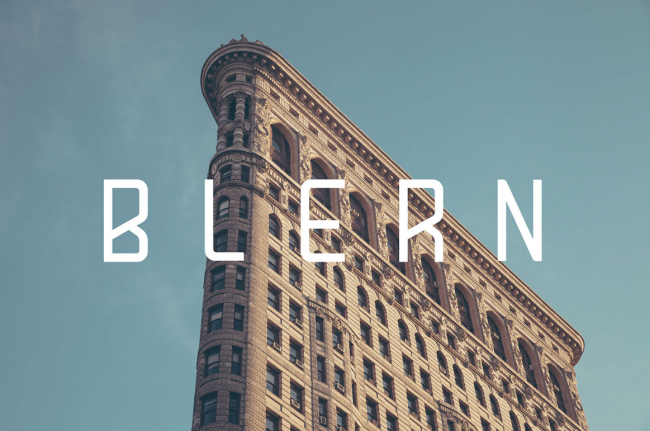
デザイナーにおすすめの、クリエイティブなフリーフォント20個を紹介します。
いずれもオリジナリティのあるデザインが特徴です。他とは一味違う、独創性のあるデザインになります。
Blern
モダンなデザインのセリフフォントです。ビジュアルデザインに合わせやすい、安定したバランスです。
Bajern
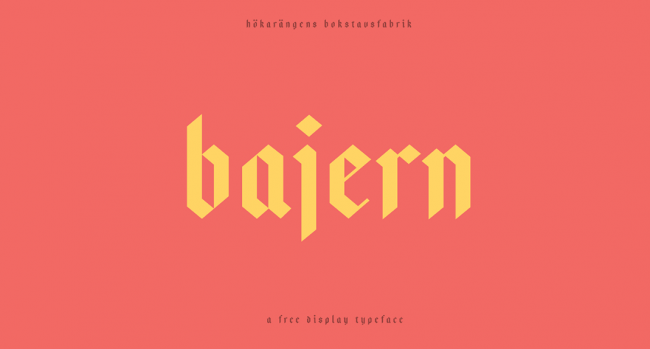
Bajern
直線でデザインされた、オリジナリティのあるデザインのフォントです。写真ギャラリーなどのモダンなデザインに合います。
Break
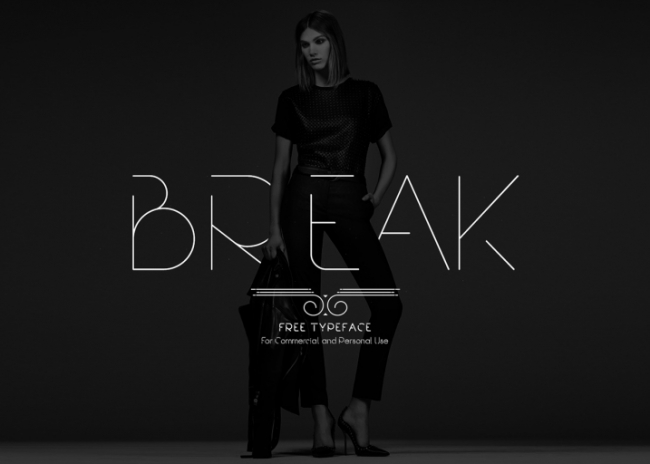
Break
Anurati
文字が欠けているという、とても独創的なデザインのフォントです。デザインに、神秘性と未来的なイメージを出すことができます。
Glamor
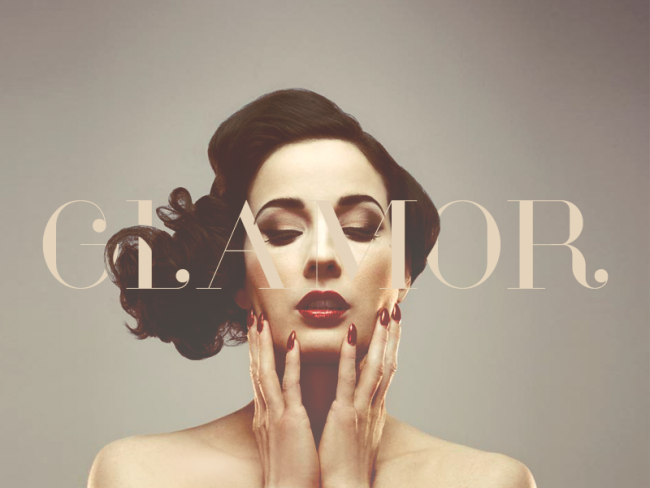
Glamor
モダンでエレガントなデザインのフォントです。デザインに高級感を出したいときにおすすめです。
Yikes
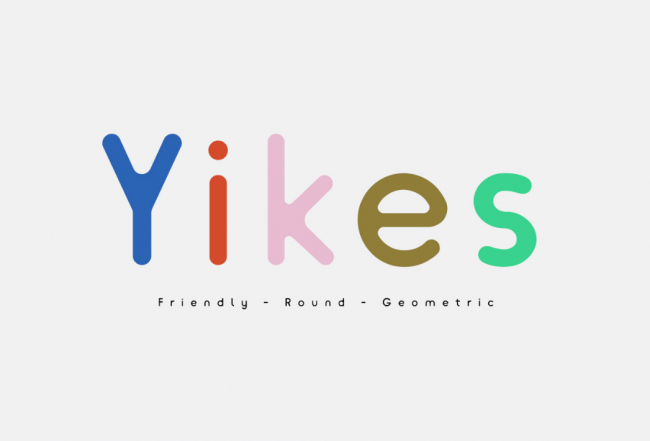
Yikes
先端や繋ぎ部分の丸みが特徴的な英語フォントです。ロゴやプロダクトデザインにもよく合います。ダウンロードリンクが小くなっていますが、「STEP 2: DOWNLOAD THE FILE HERE –> CLICK」と書かれている部分からダウンロードできます。
Soria
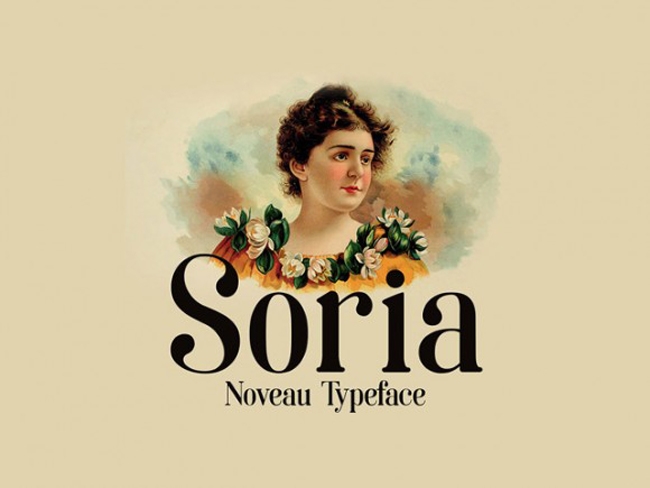
Soria
かわいらしいデザインのフリーフォントです。古典的でり、同時にモダンな印象のあるフォントです。
Carosello
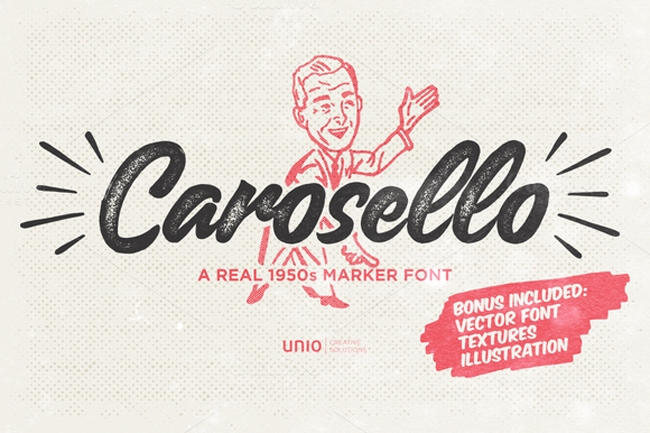
Carosello
太字の筆記体風の斜体デザインが特徴的なフォントです。ポップでヴィンテージ感のあるデザインによく合います。
Slot
文字の途中に隙間がある、独創的なデザインのフォントです。このフォントを使うだけでデザインにオリジナリティが生まれます。
Bushcraft
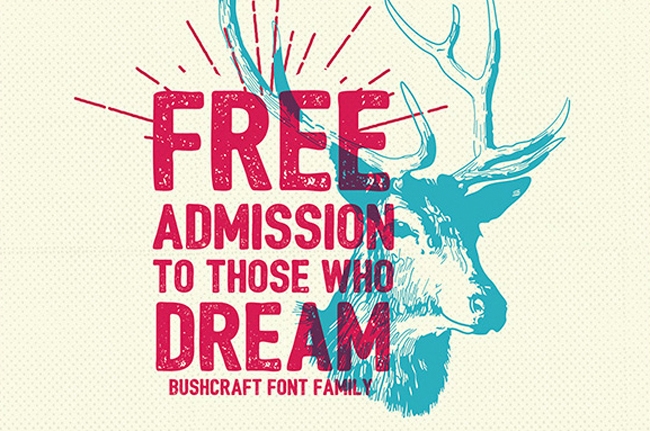
Bushcraft
ヴィンテージな印象の太めのフォントです。デザインにインパクトが出ます。
Knile
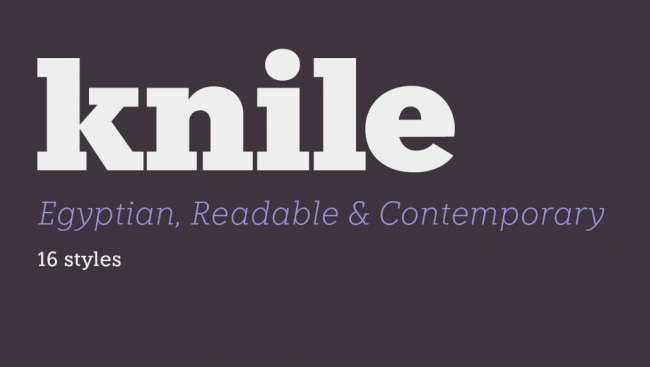
Knile
Wayward
万年室で書いたような、上品な印象の英字フォントです。ロゴバッジのデザインに合います。
ONE DAY
モダンなデザインのフリーフォントです。都会のイメージによく合います。
Arabella